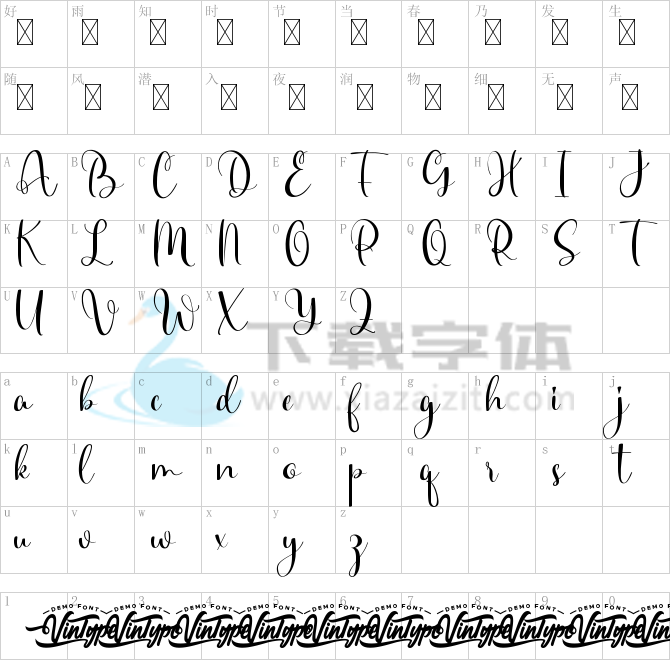
Always Funny Demo Script.ttf字体下载,这款字体结构工整、笔画清晰,兼顾美观与易读性,适用于标题、正文、海报、包装、LOGO 等多种场景。字形优雅稳定,风格百搭耐看,适配日常排版与创意设计,让文字呈现更舒适、更具质感。Always Funny Demo Script.ttf字体下载一笔一画,皆是细节,以均衡的比例、流畅的线条打造舒适视觉体验,字形端正大气,风格简约现代。无论是商业设计、品牌宣传还是日常排版,都能轻松驾驭,让文字更有格调与力量。Always Funny Demo Script.ttf字体下载字体下载。